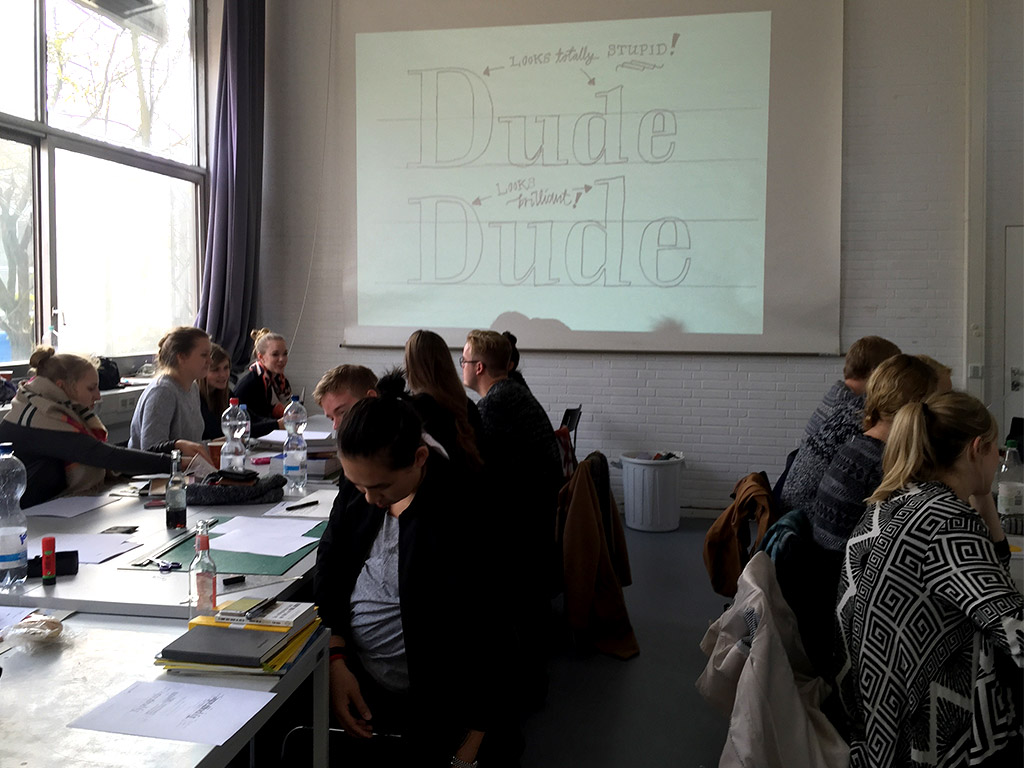
Das Seminar an der Leibniz-Universität Hannover bot einen Überblick über das Gestalten mit Schrift. Ausgehend vom Zeichen als kleinste Einheit typografischer Gestaltung bis hin zu komplexen Layouts erarbeitete ich mit den Studierenden aus den Studiengängen Architektur, Langschaftsgestaltung und Kunst folgende Themen: Typografische Grundlagen und Fachbegriffe, Schriftgeschichte, Klassifizierung von Schriften, Mikrotypografie und Anwendung von Schrift im digitalen Medium. Begleitend zu Vorträgen und Workshops wurden die Inhalte anhand themenspezifischer Aufgabenstellungen in Form von Layouts umgesetzt.